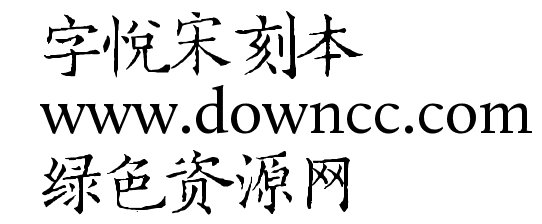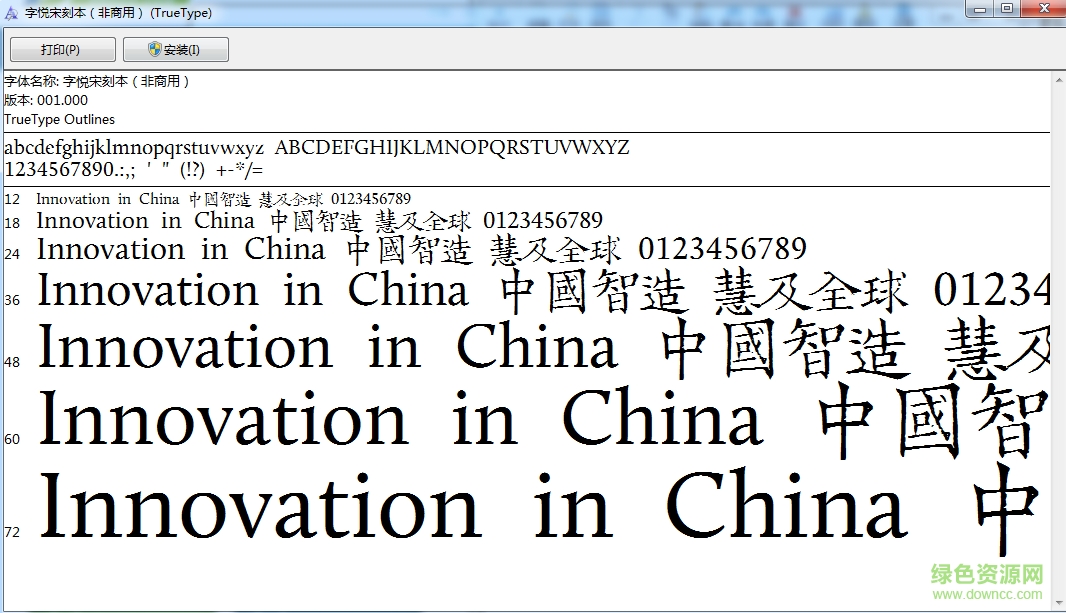
字悅宋刻本簡體ttf是一款非商業(yè)使用的簡體中文字體,清秀簡潔的字跡讓廣大排版設(shè)計、書面印刷、廣告創(chuàng)意的人群深為喜愛,歡迎大家在綠色資源網(wǎng)免費下載使用!
復(fù)刻的宋刻本字體,本字型字源來自于中國國家圖書館藏書,南宋咸淳廖氏世彩堂刻本《昌黎先生集》,其字的書法風(fēng)格令人想起唐代大師褚遂良和柳公權(quán)。本字處理方法是采取保留其“神”意,使其更顯古樸。這是本人第一次復(fù)刻古代刻本字型,其從原刻本整書提煉的單字約有1800個字,之后的字用的是仿制加拼合“大法”,項目起始時間為2016年3月,國標(biāo)6763字完成于九月,截至目前收字7816個單字,包括部分異體字,但目前只有繁體字。